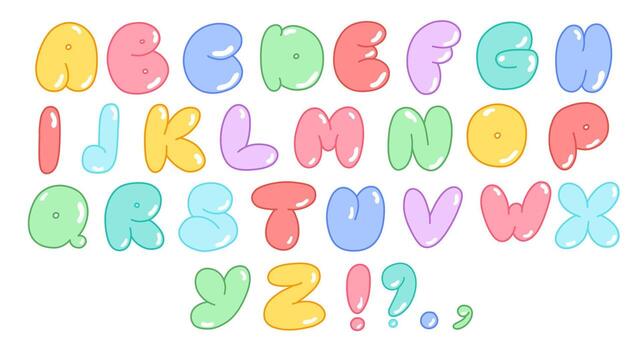
Bubble font Việt hóa là nhóm phông chữ thuộc dòng Display ngộ nghĩnh, mô phỏng sinh động những quả bong bóng căng tròn hoặc những thanh kẹo ngọt ngào với các góc bo mềm mại và độ nở phồng tối đa. Mang vẻ ngoài tươi vui, đầy ắp năng lượng và tính giải trí, kiểu chữ này giúp các kiến trúc sư, nhà thiết kế thổi bùng sắc thái rực rỡ vào các bản vẽ phối cảnh khu vui chơi trẻ em, tiệm bánh ngọt container hay các biển hiệu homestay gia đình.
Đường nét căng phồng tròn trĩnh và năng lượng tươi vui của Bubble font Việt hóa
Điểm cuốn hút của Bubble font Việt hóa nằm ở cấu trúc hình thể không góc cạnh, nơi các con chữ như được bơm căng không khí, tạo cảm giác thân thiện và cực kỳ an toàn cho thị giác người nhìn. Độ dày dặn của các khối chữ mang lại khả năng chiếm lĩnh không gian hiển thị vượt trội, khiến các tiêu đề lập tức trở thành tâm điểm của sự chú ý.
Sự ổn định về mặt cảm xúc của dòng font này giúp khơi gợi niềm vui, sự tò mò và cảm giác thư giãn cho người sử dụng không gian. Khi xuất hiện trên các bề mặt vật liệu hiện đại như tấm panel tôn phẳng sơn màu tươi sáng, nhựa mica bóng hay các chi tiết kim loại uốn cong trong nhà lắp ghép, Bubble font tạo nên sự tương phản thú vị với các kết cấu xây dựng vuông vức.
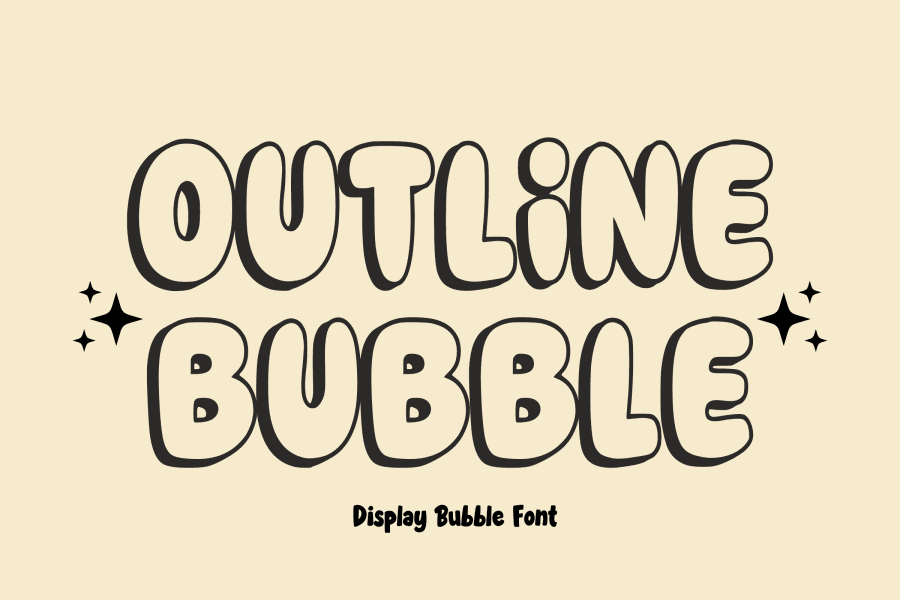
| Phân loại phong cách | Bubble Display / Rounded / Puffy Cartoon |
| Mục đích phù hợp | Biển tên khu vui chơi, poster thiếu nhi, logo tiệm kem |
Tư vấn từ chuyên viên: Bubble font sở hữu tạo hình căng mọng và độ phủ bề mặt rất lớn. Để bản thiết kế đạt hiệu quả thẩm mỹ tốt, bạn chỉ nên sử dụng phông chữ này cho các tiêu đề chính, tên thương hiệu hoặc khẩu hiệu ngắn.
03 Ứng dụng phông chữ Bubble vào công trình thực tế
Nhờ vẻ ngoài ngộ nghĩnh và tính gợi hình phong phú, bộ phông chữ này mang lại giá trị thực tế lớn trong khâu tạo điểm nhấn cho các công trình hiện đại:
- Biển hiệu mặt tiền cho Tiệm Kem và Trà sữa Container: Những khối chữ phồng to của Bubble font rất ăn ý khi gia công chữ nổi bằng mica bóng gắn đèn LED hắt sáng, mang lại diện mạo ngọt ngào, thu hút các gia đình và bạn trẻ ghé thăm trải nghiệm.
- Hệ thống biển tên phân khu Khu vui chơi và Trường mầm non: Phông chữ này khi in trên các bảng alu màu pastel hoặc decal dán kính sẽ giúp không gian trường học lắp ghép toát lên sự thân thiện, tạo sự hào hứng cho các bé mỗi ngày đến lớp.
- Trang trí góc sinh hoạt phòng ngủ của bé: Bạn có thể dùng phông chữ này để cắt xốp dán tường hoặc làm bảng tên góc học tập, mang đến bầu không khí ấm cúng và kích thích trí tưởng tượng sáng tạo của trẻ nhỏ.
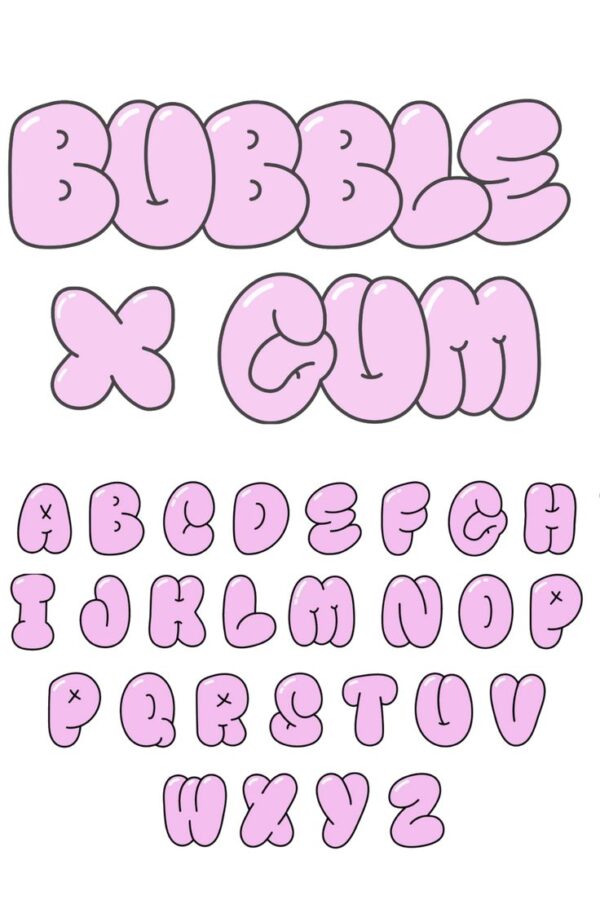
03 Lưu ý bố cục tải font chữ Bubble Việt hóa luôn sinh động và rõ nét
Để khai thác hiệu quả vẻ đẹp của dòng font bong bóng này mà không gây cảm giác bí bách cho bản vẽ, người thiết kế nên lưu tâm một số kinh nghiệm sau:
- Nới rộng khoảng cách ký tự (Tracking): Do các con chữ có độ phồng to về mọi hướng, các ký tự rất dễ chạm vào nhau. Bạn nên kéo giãn nhẹ khoảng cách giữa các chữ cái để bố cục được thông thoáng, tránh hiện tượng dính nét khi in ấn ở cự ly xa.
- Hạn chế dùng cho đoạn văn bản dài: Độ dày nét lớn của tải font chữ Bubble Việt hóa không phù hợp cho các đoạn văn bản giải thích chi tiết. Hãy giới hạn trong các cụm từ ngắn từ 2 đến 4 từ để tạo điểm nhấn thị giác tập trung.
- Kết hợp cùng bảng màu kẹo ngọt: Bubble font phát huy hiệu quả thị giác cao khi phối cùng các tông màu tươi tắn như hồng phấn, vàng bơ, xanh bạc hà hoặc cam đào, giúp tôn vinh tinh thần vui tươi và ngọt ngào của bộ chữ.
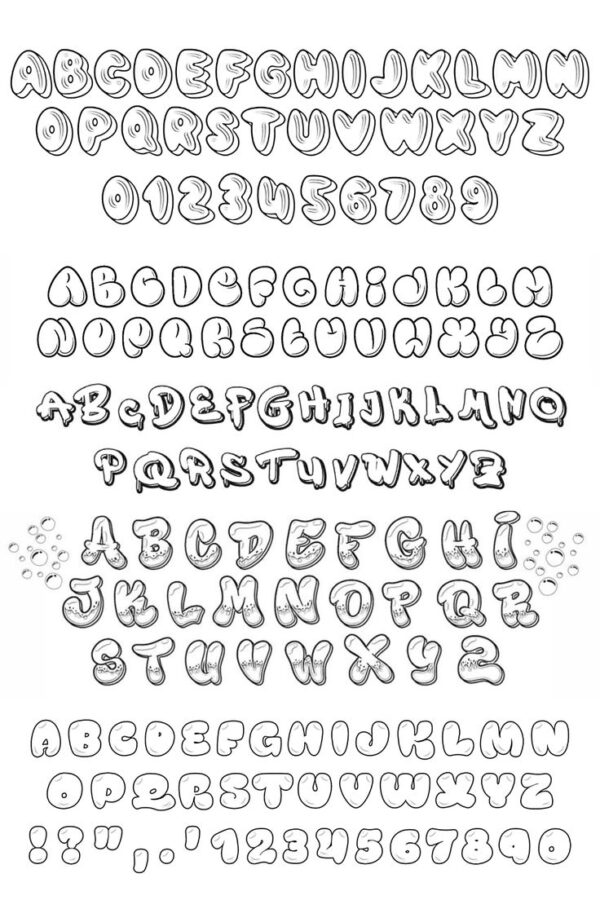
1. Font Bubble có dùng được trên ứng dụng Canva không?
2. Phông chữ này có hỗ trợ đầy đủ các ký tự số không?
Có. Bộ phông Bubble đã được tích hợp đầy đủ hệ thống chữ số với hình khối căng tròn đồng điệu, rất thuận tiện cho việc trình bày số phòng homestay hay bảng giá đồ uống.